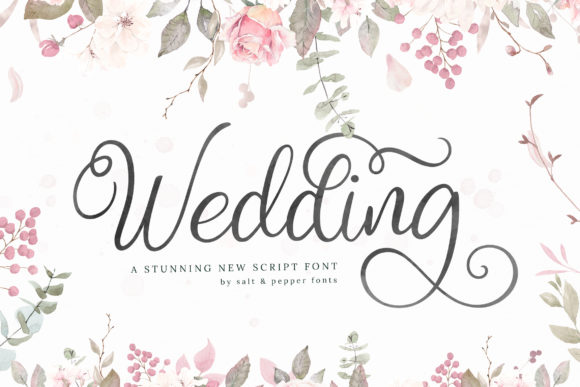
Wedding Script
Wedding Script: A Fonte Que Transforma Seu Projeto em Pura Elegância
Se você está em busca de uma tipografia que una romance, sofisticação e um toque de luxo, a Wedding Script é a escolha perfeita. Desenvolvida em estilo caligráfico, cada letra parece dançar suavemente ao longo da linha de base, criando uma sensação de movimento e delicadeza que encanta à primeira vista.
- Design romântico e doce – Ideal para convites de casamento, cartões de felicitações e branding de eventos especiais.
- Ligaduras e glifos exclusivos – O suporte PUA (Private Use Area) permite acessar rapidamente uma variedade de ligaduras e caracteres alternativos, proporcionando ainda mais criatividade ao seu layout.
- Versatilidade de uso – Funciona perfeitamente em projetos digitais e impressos, desde sites de noivas até materiais de papelaria de alto padrão.
- Leitura agradável – Apesar do estilo caligráfico, a fonte mantém ótima legibilidade, o que garante que sua mensagem seja compreendida sem esforço.
Ao escolher Wedding Script, você não está apenas adicionando uma tipografia ao seu projeto; está inserindo uma experiência visual luxuosa que transmite amor e cuidado em cada detalhe. Seja para um convite de casamento tradicional ou para um branding contemporâneo, esta fonte eleva instantaneamente o nível de sofisticação.
Por que a Wedding Script deve estar no seu kit de design?
1. Impacto emocional – As curvas suaves e as ligaduras artísticas criam uma conexão emocional imediata com o público.
2. Flexibilidade criativa – Use as variantes de glifos para personalizar títulos, assinaturas ou monogramas exclusivos.
Em resumo, a Wedding Script traz aquele toque de magia que todo projeto romântico merece. Não perca a oportunidade de transformar suas criações com esta fonte premium e faça cada palavra brilhar como um verdadeiro conto de amor.